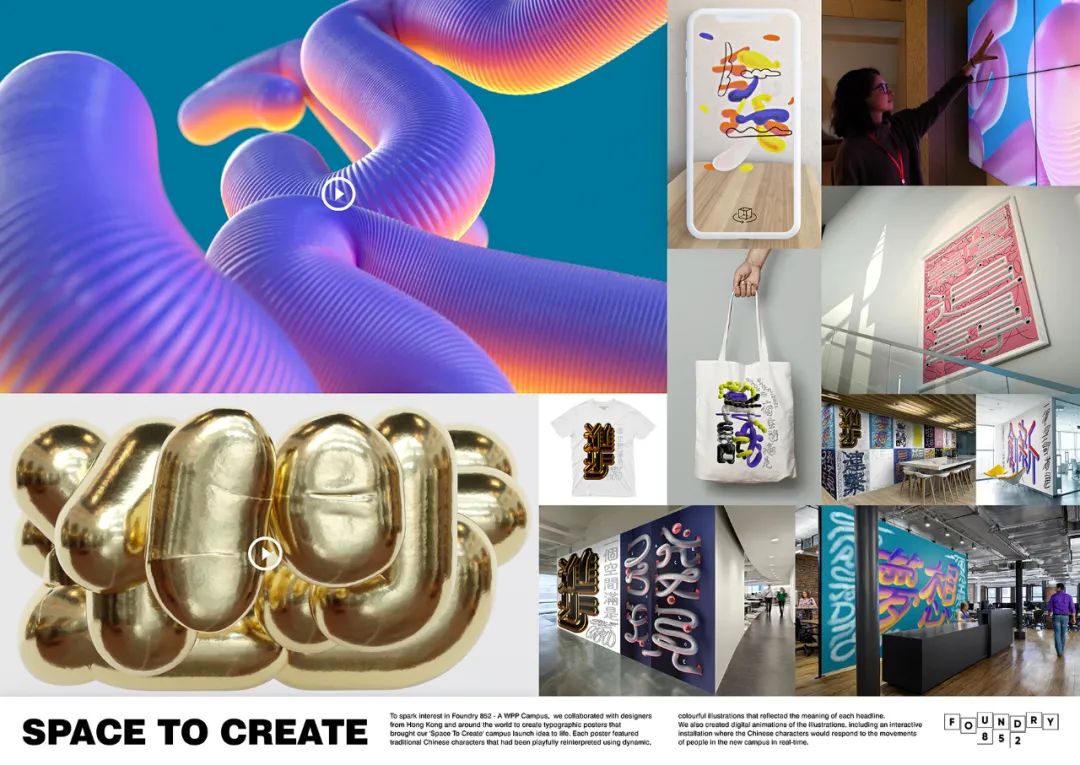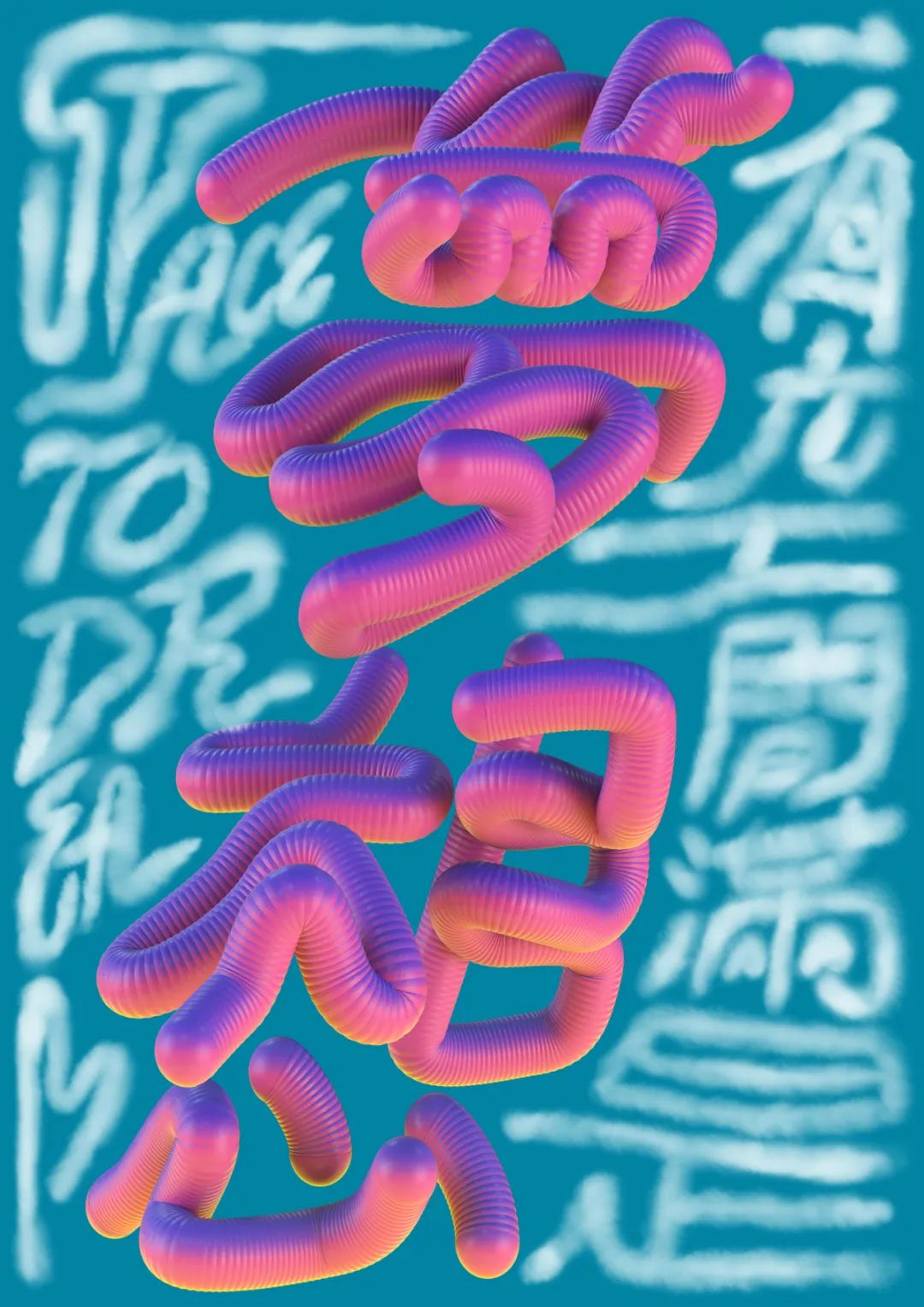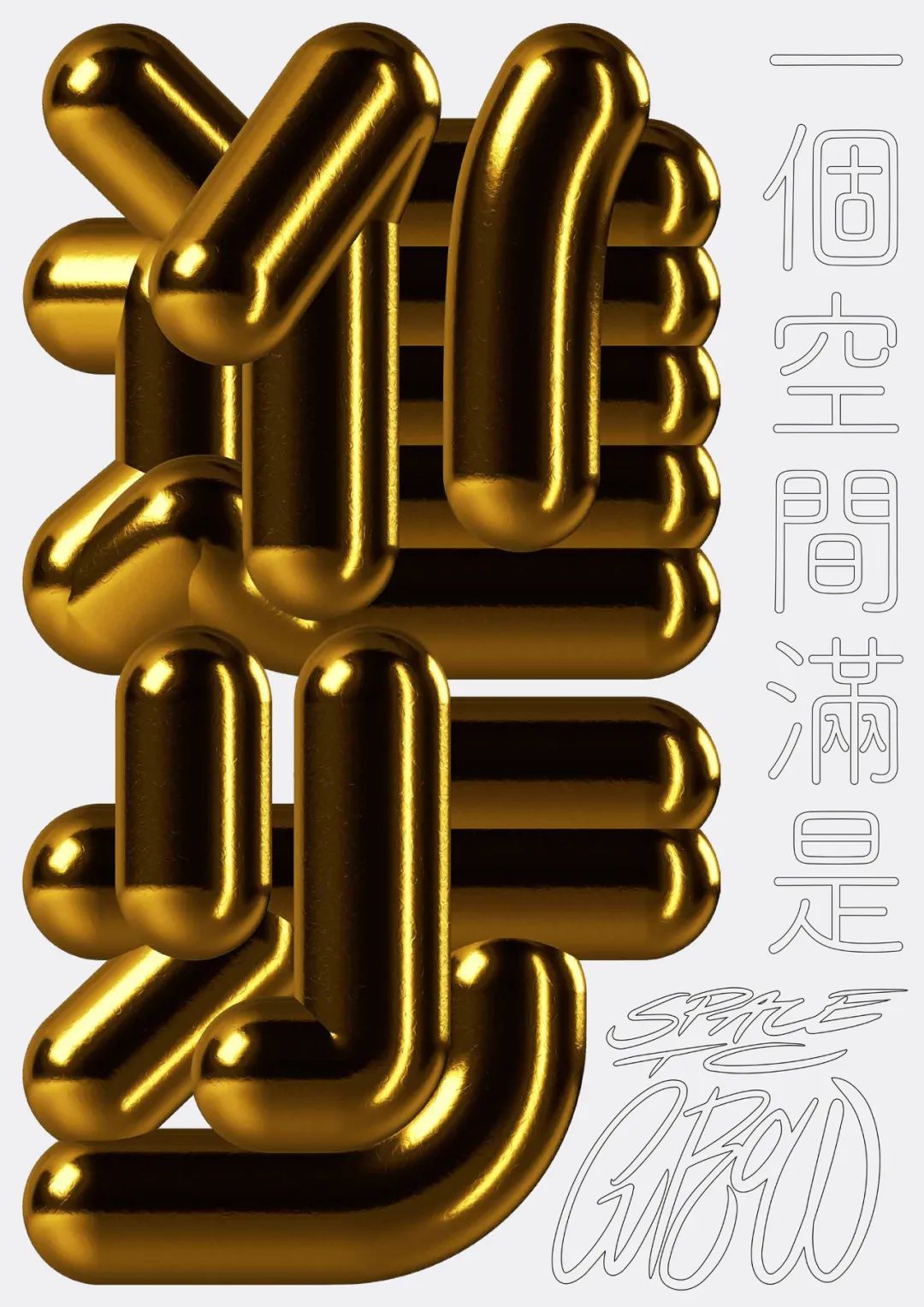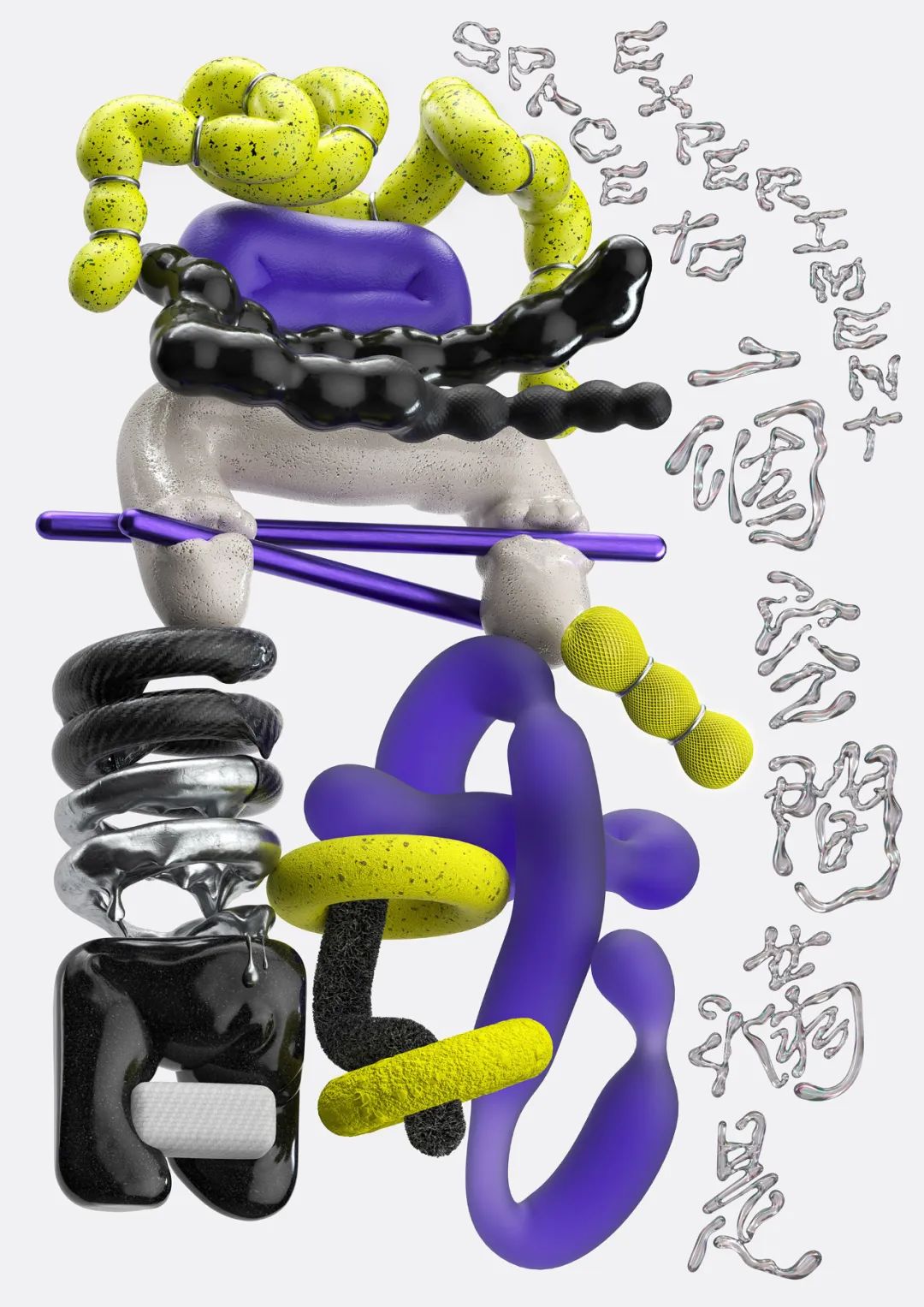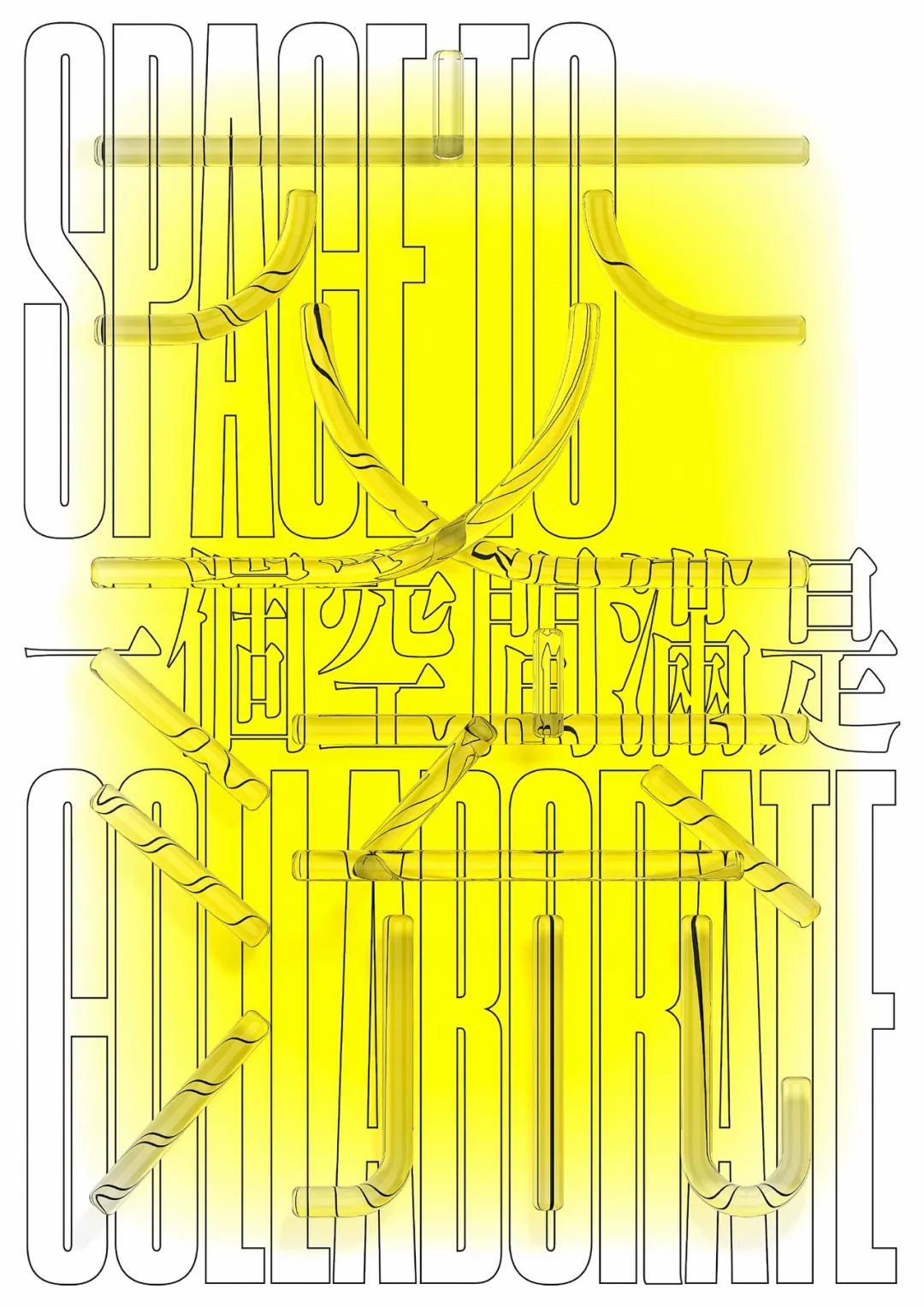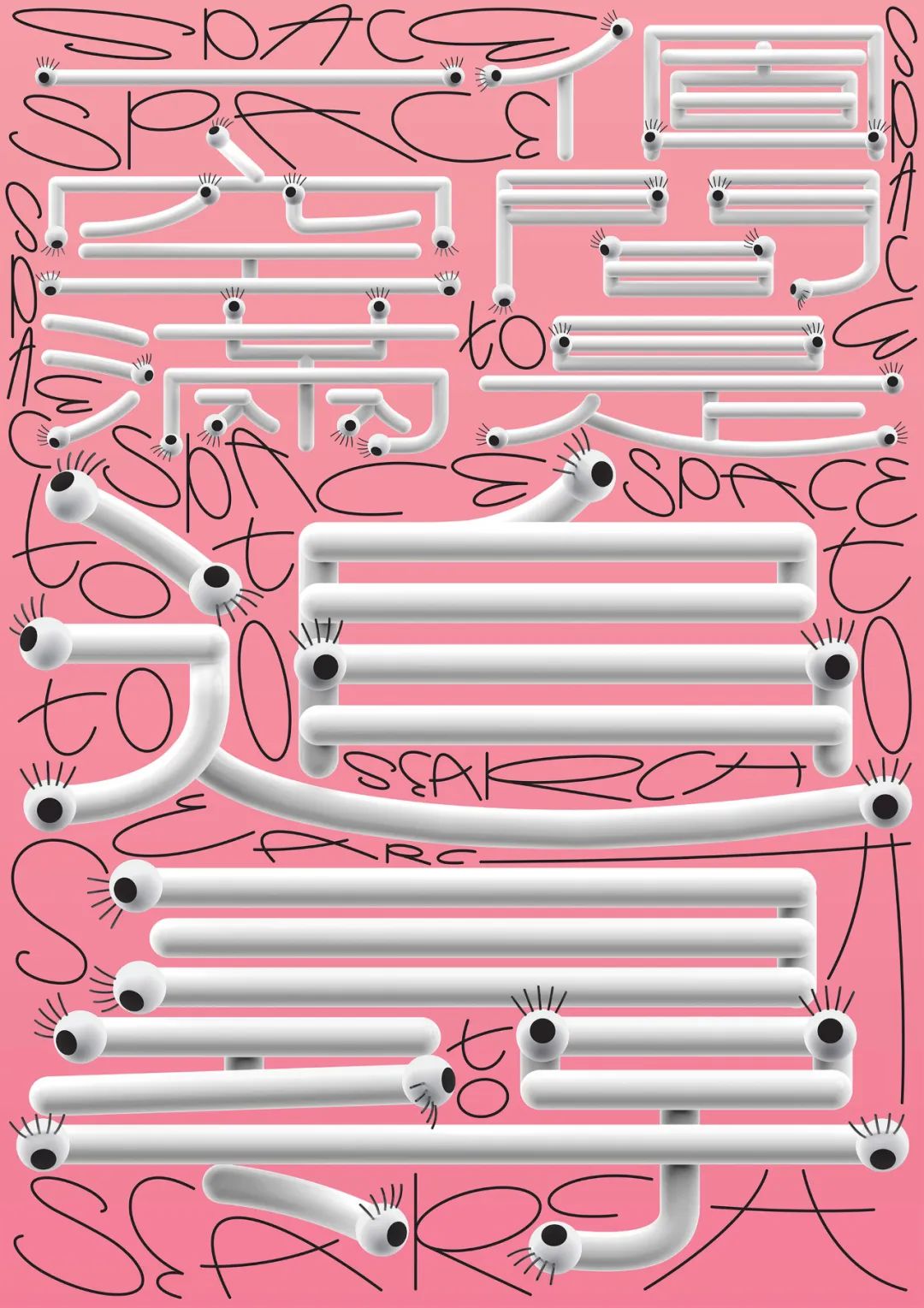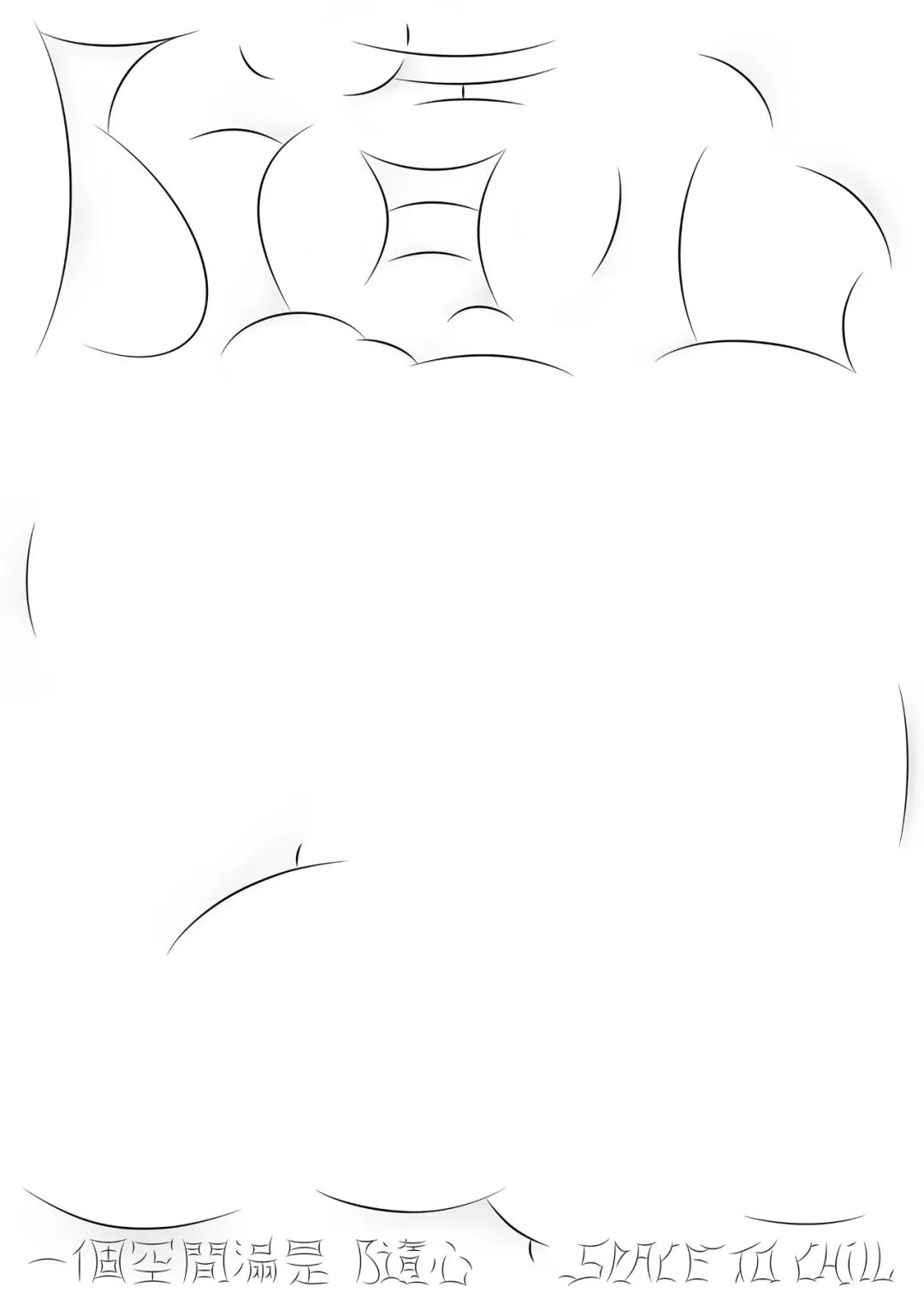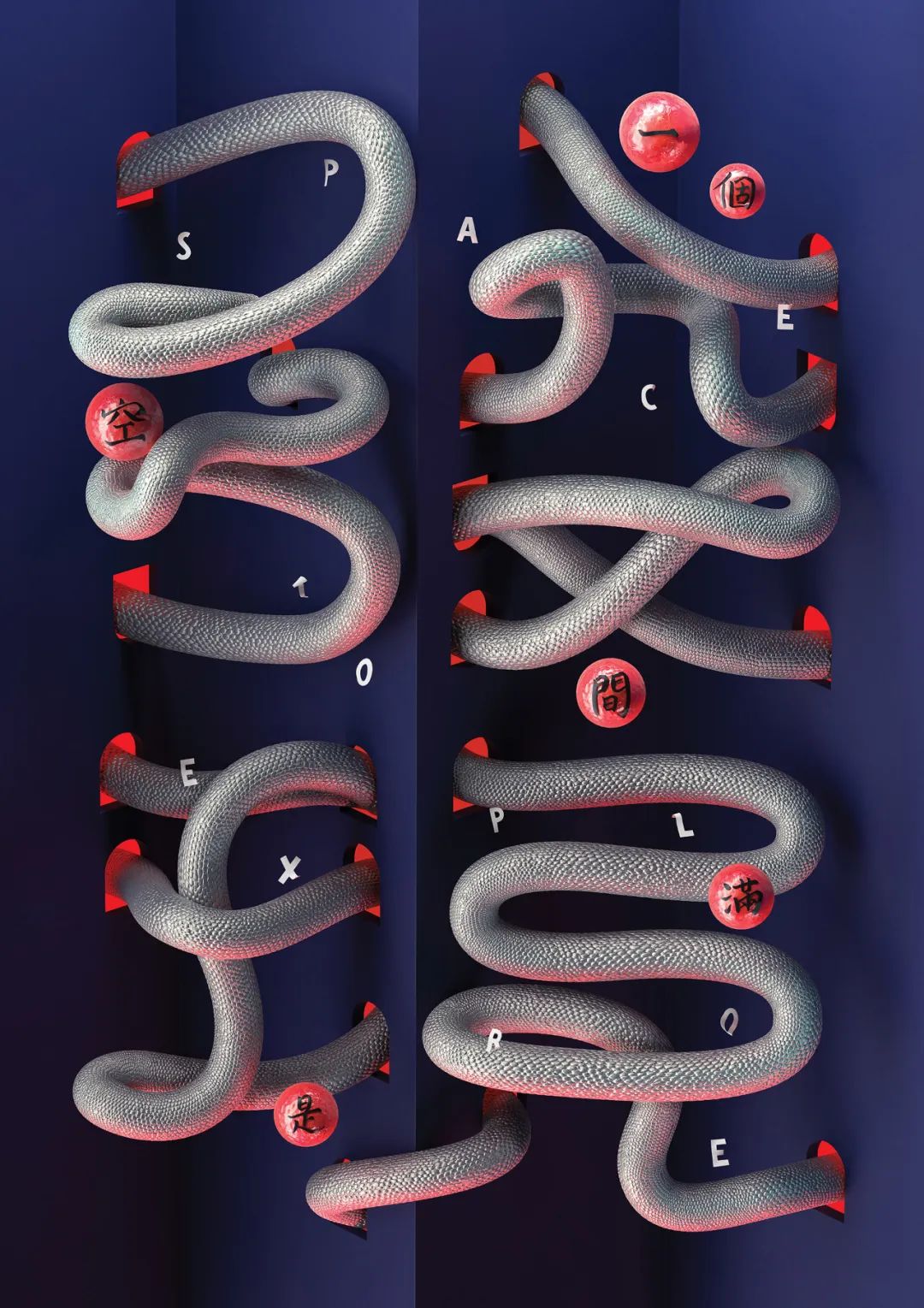
都是字的海报,柚子之前发过很多,它们大多会弱化识别性,而是从创意出发,把字拆解为元素、符号,而今天说的这个Foundry 852,直接把文字玩出了花~
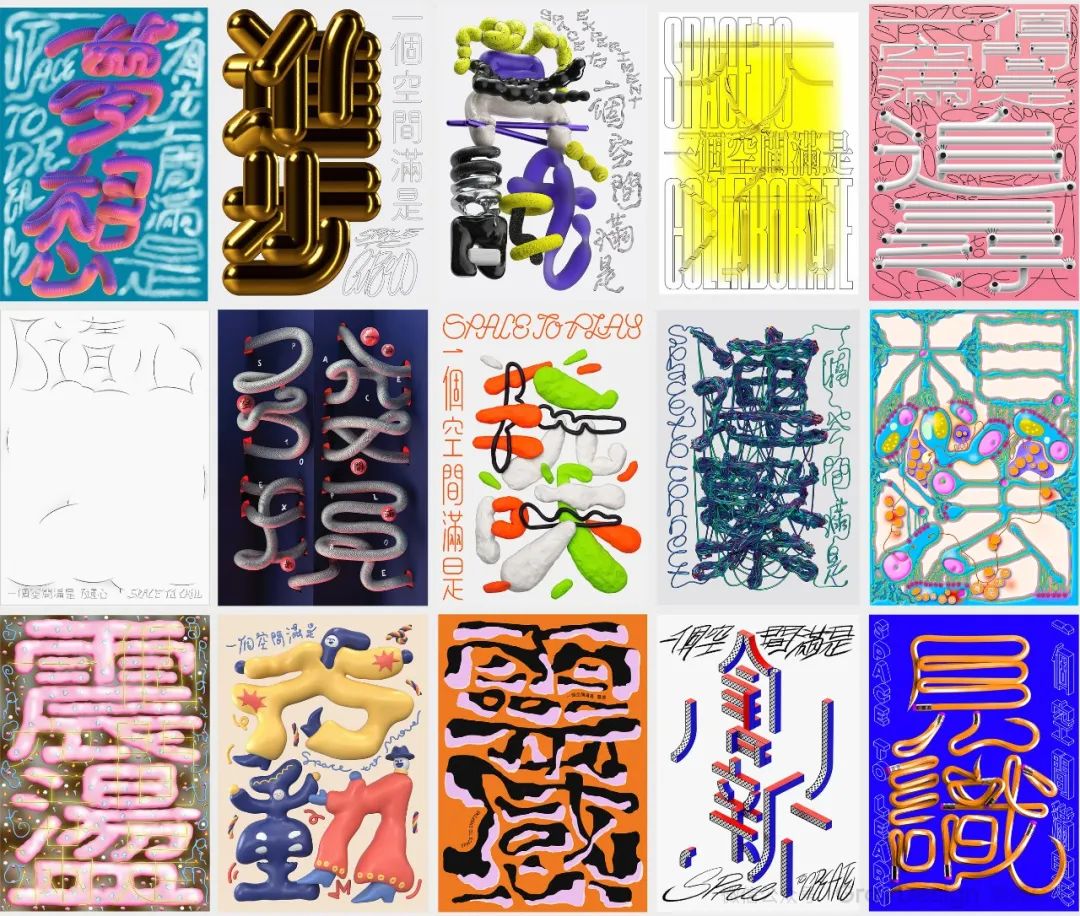
来看看这15幅天马行空的系列海报,都是由WPP集团旗下的香港奥美和来自世界各地的设计师合作推出的。
它们都围绕着Space to XX(一个空间满是XX)这个主题,在中国繁体汉字的基础上,通过各种天马行空的想象,描绘出15组梦想、进步、尝试、交流、追寻、随心、发现、玩味、连系、想法、震荡、行动、灵感、创新、见识。
一个空间满是梦想
Space to Dream
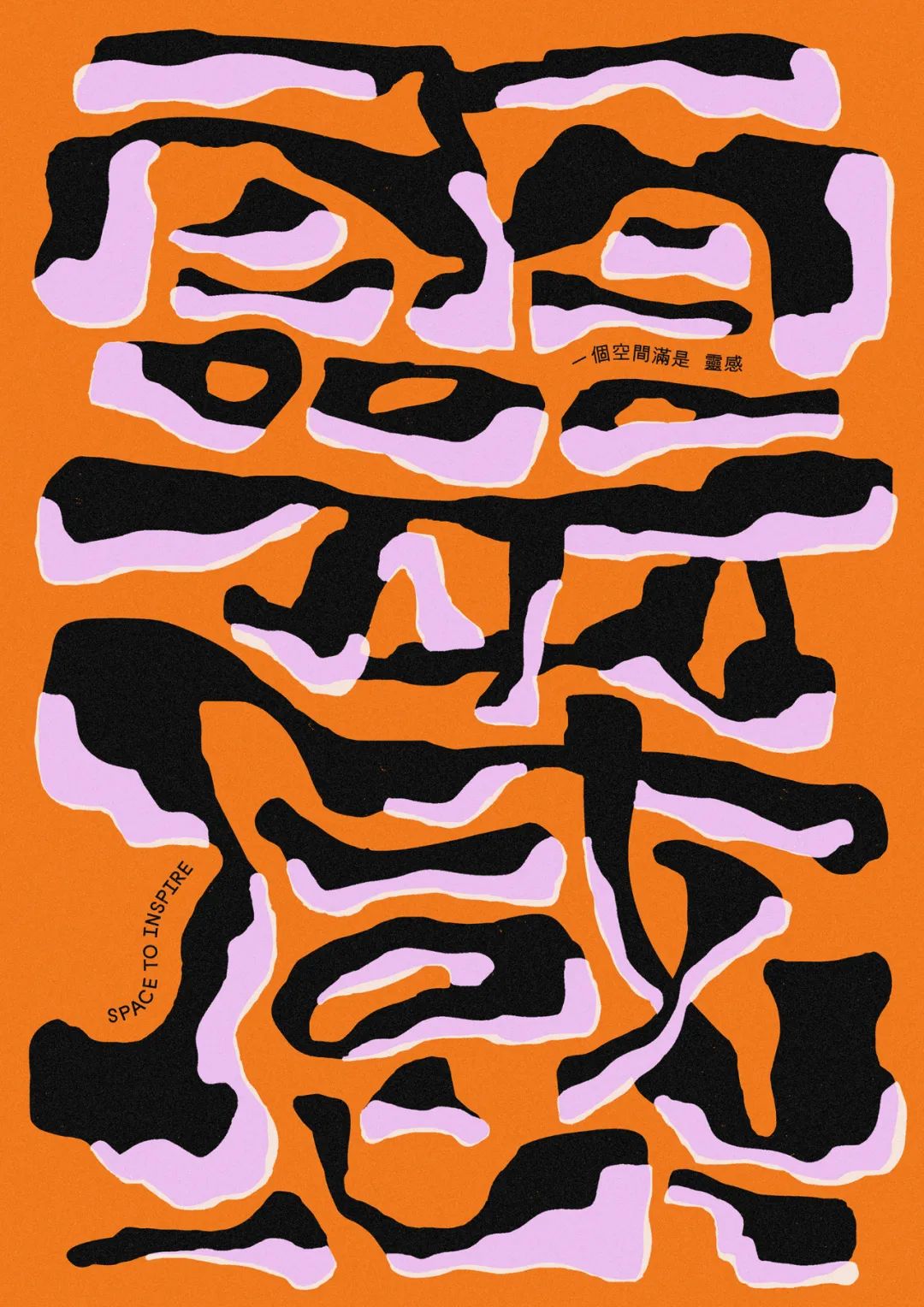
一个空间满是进步
Space to Grow
一个空间满是尝试
Space to Experiment
一个空间满是交流
Space to Collaborate
一个空间满是追寻
Space to Search
一个空间满是随心
Space to Chill
一个空间满是发现
Space to Explore
一个空间满是玩味
Space to Play
一个空间满是连系
Space to Connect
一个空间满是想法
Space to Think
一个空间满是震荡
Space to Brainstorm
一个空间满是行动
Space to Move
一个空间满是灵感
Space to Inspire
一个空间满是创新
Space to Create
一个空间满是见识
Space to Learn